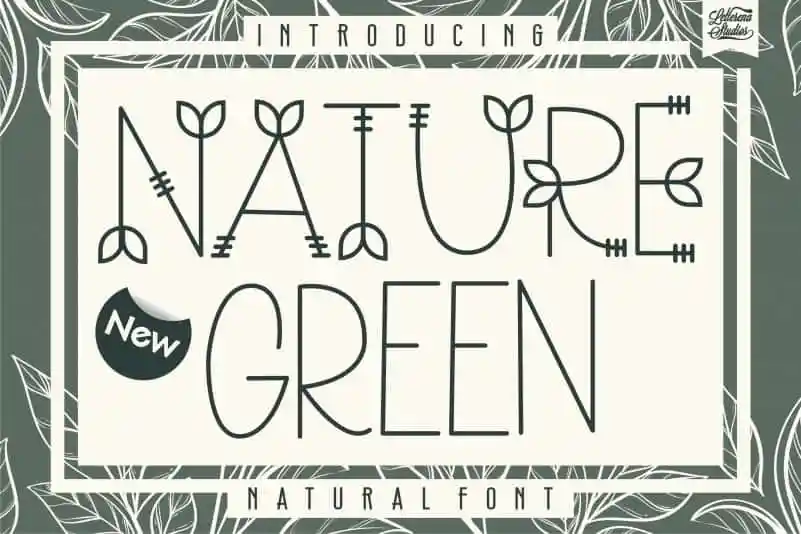
Nature Green Display Font – Fonte Grátis
Nature Green Display Font
A Nature Green Display Font é uma elegante e simples fonte feita à mão com letras góticas, projetada para enriquecer seu acervo de fontes de forma agradável e versátil. Seja você criando um layout informativo ou personalizando uma mensagem de marketing, esta fonte irá adicionar um toque distintivo que transformará qualquer projeto em destaque. Com um design prático e intuitivo, ela pode ser usada para destacar títulos, headlines ou gráficos, oferecendo um equilíbrio perfeito entre elegância e praticidade. E como qualquer boa fonte de leitura, a Nature Green Display Font também é fácil de ler em grandes dimensões, tornando-a uma escolha ótima para uso online e impressão profissional.